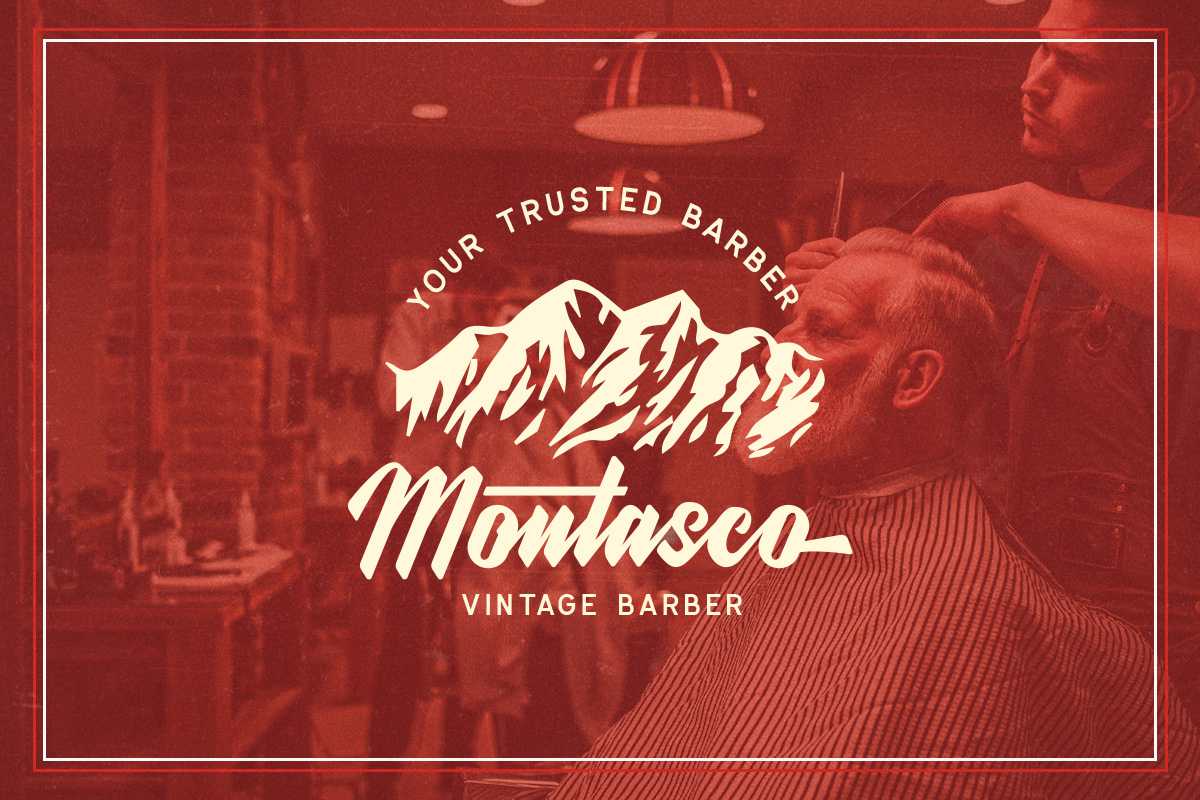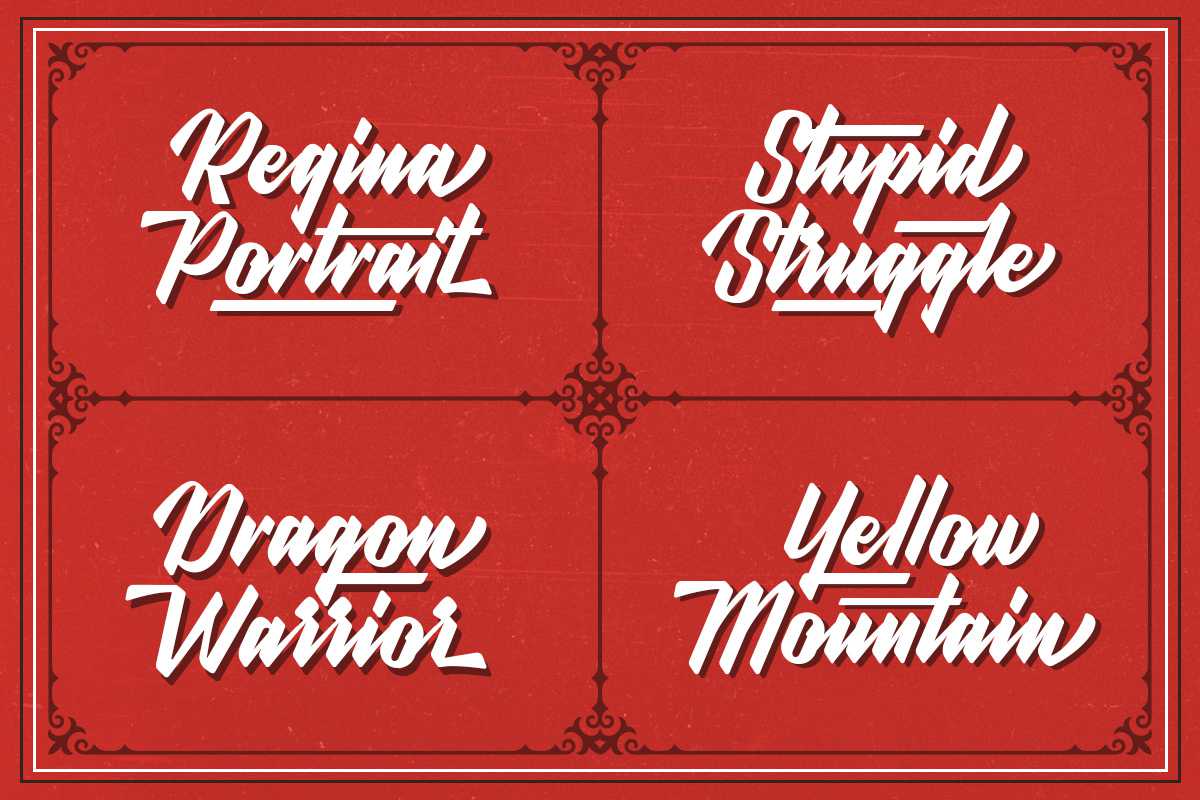
WonderStark,属于一种具有强烈和粗体特征的字体。该字体适用于InLogotype/wordmark、徽章、招牌、海报、头条文字、服装、婚礼宣传等,具有多种开放式功能,包括:模仿、风格替换、上下文替换、swash等,并支持多种语言。WonderStark,属于具有强烈和粗体特征的自定义字体。此字体适用于非自定义字体/文字标记、徽章、招牌、海报、头条文字、服装、婚礼宣传等。它具有多种开放式功能,包括开放式、文体替换、上下文替换、swash等,并支持多种语言。